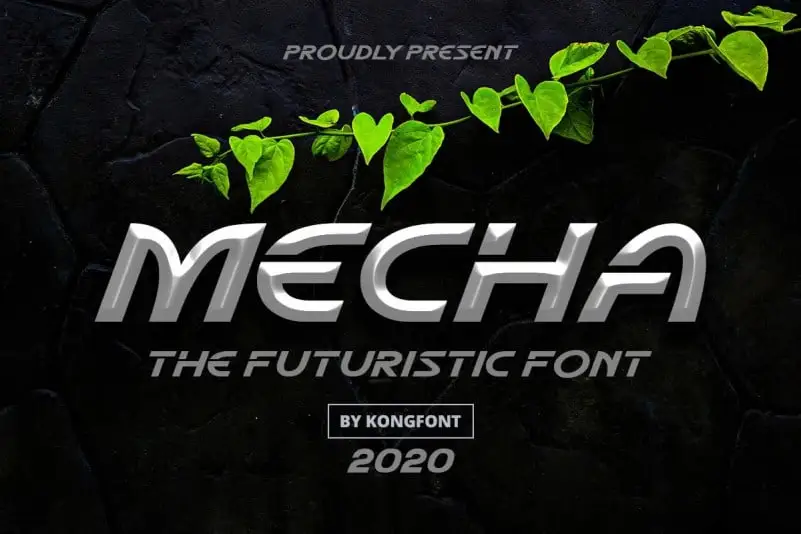
Mecha Display Font – Download Grátis
A fonte ‘Mecha Display Font’ é uma elegante serif alta endereço que traz um toque luxuoso e sofisticado. Ela foi criada por fontkong para aqueles buscando um charme único no seu design visual. Este tipo de texto, com suas linhas levemente arredondadas e traços detalhados, é perfeito para destacar o que de melhor há em qualquer projeto, mas sempre oferecendo uma perspectiva distinta e originalmente ‘mecânica’. Perfeito para criar mensagens impactantes e um design visual único. A font ‘Mecha Display Font’ surge como a escolha ideal para quem busca transpor o sofisticação da alta-costura em textos digitais. Seja para uma identidade visual ou para um projeto gráfico de destaque, essa fonte é certamente um investimento que vale cada centavo.